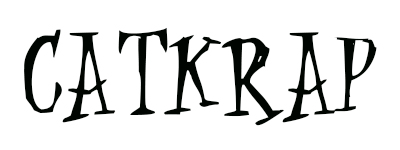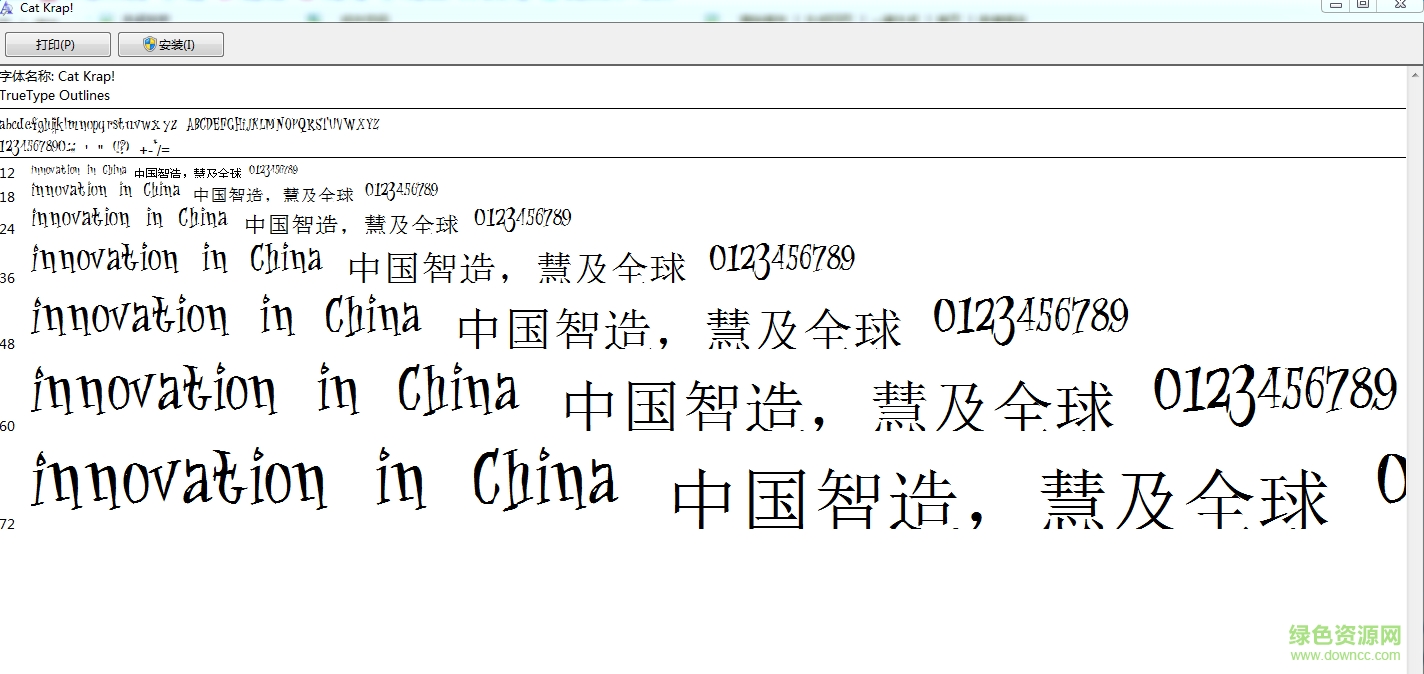
catkrap字體是一款Catkrap風(fēng)格的英文字體軟件,Catkrap風(fēng)格的字體給人非?;母杏X(jué),深受廣大年輕人的喜愛(ài),還有更多好看字體盡情期待,歡迎到綠色資源網(wǎng)下載體驗(yàn)!
catkrap是一款Catkrap風(fēng)格的英文字體,字體效果比較滑稽,喜歡Catkrap風(fēng)格英文字的朋友可以下載使用看看效果如何。